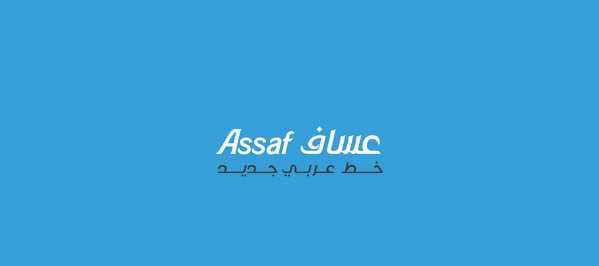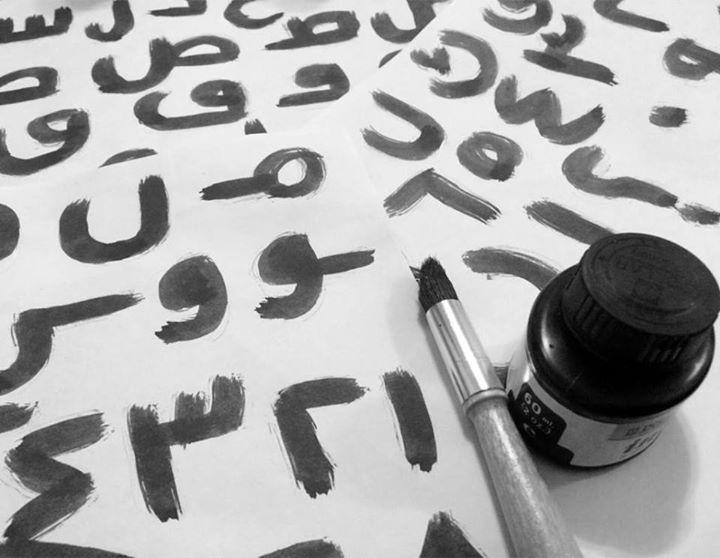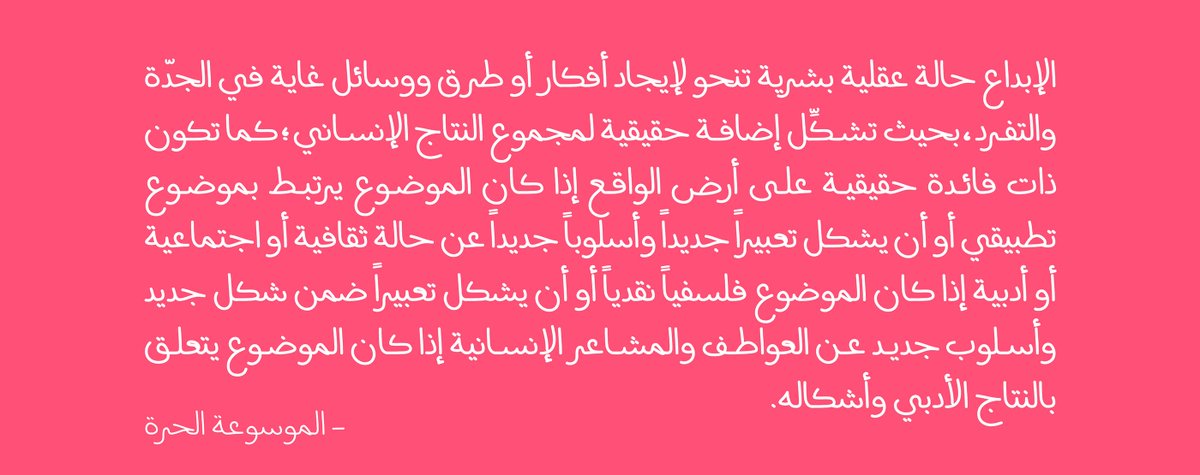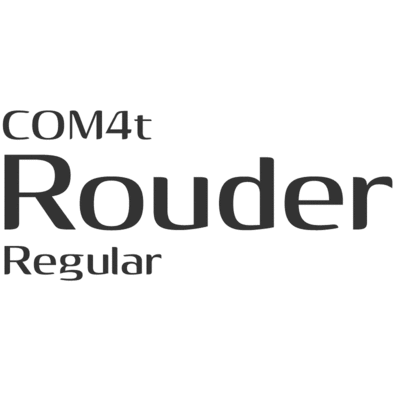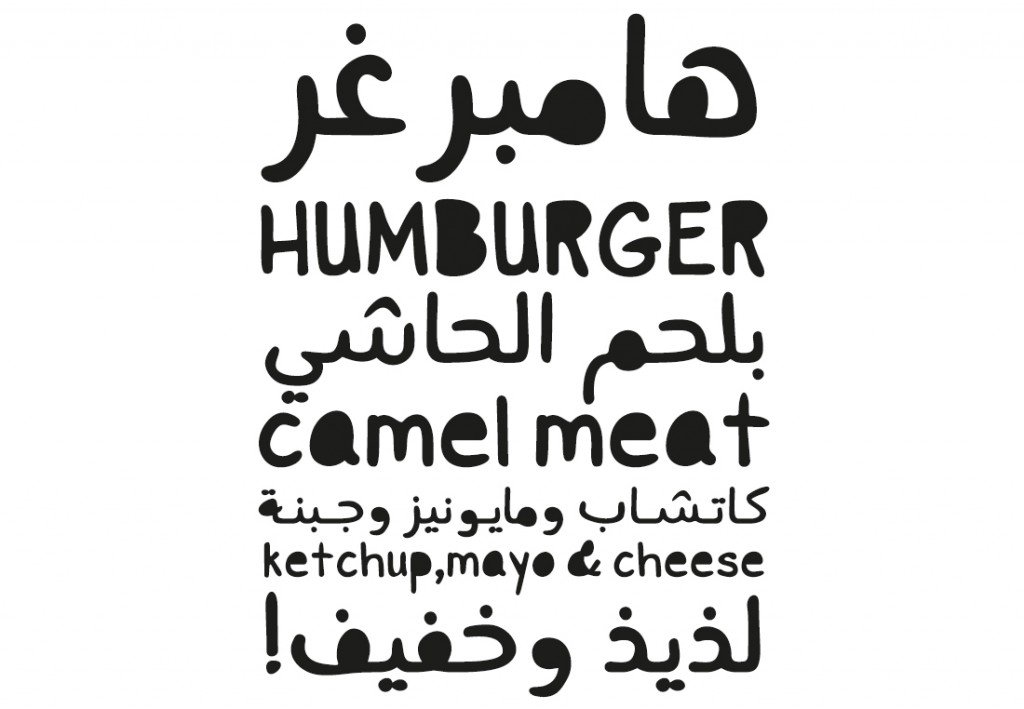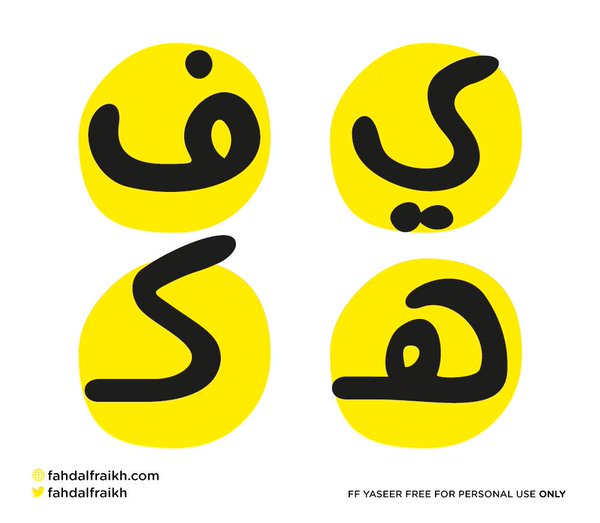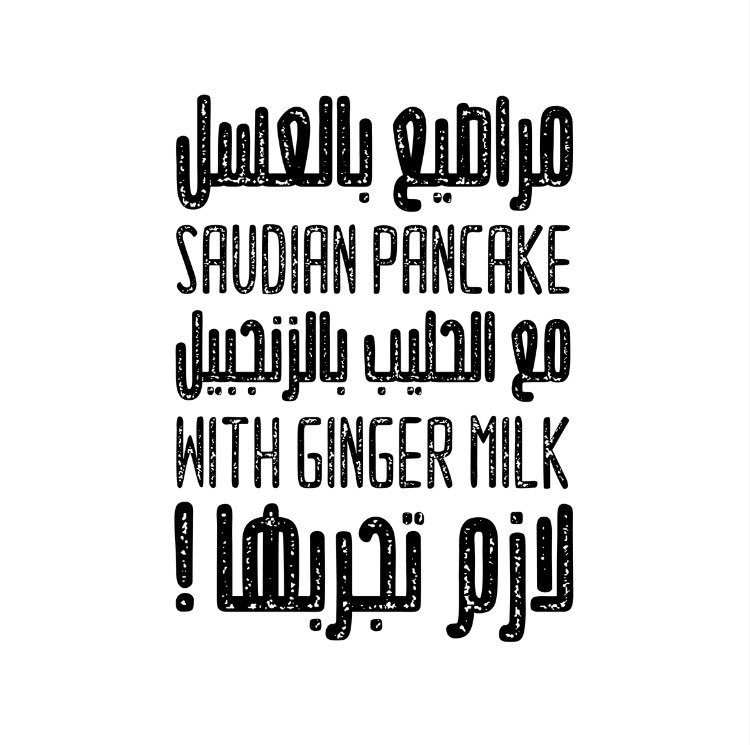
خطـــوط عربية وإنجليزية جميلة للتحميل المجاني، والمدفوع
خط عربي جديد للمصمم عساف القرني تحميل مباشر من هنا
خط ذياب تصفح من هنا جمالياته وأيضاً لشراءه
بوية | خط عربي بالفرشاة والألوان
(ملهم) خط عربي جديد، مستوحى من خذ اليد البسيط للتحميل
COM4t Rouder Regular
Yaseer Typeface
يسير .. خط مكتوب باليد
خط طويل | لـ فهد الفريخ
خط عربي مجاني مقدم من شركة وسم
خط مجاني ( ALEO ) نرجو أن ينال استحسانكم
خط طباعي ساخر صُنع من 76 علامة تجارية متميزة، من تنفيذ استوديو Hello Velocity الإبداعي.
خط مركزي من خطوط النسخ الجديدة المميزة
حكاية Hekaya
خط يدوي لـطيف يدعم العربية و اللاتينية، يتكون من ثلاثة أوزان: رفيع “مجاني” ،عادي وسميك
خطوط انجليزية جديدة يجب ان تمتلكهم
المبدع المغربي ياسر داحس
ينتج ثلاث خطوط عربية
خطوط جديدة مميزة
خط كوفام هو أحد خطوط مشروع الماتشميكنغ الخمسة للإصدار 2
تصميم وائل مرقص , آرثر شمال , والمهندس المعماري ريتشارد واغنر
عارف رقعة/ الخط الأكثر شعبية ودائما مايتم سؤالنا عنه
ويستفاليا / خط طباعي
تمت صناعته من وحي خط اليد
عدد كبير من الخطوط الانجليزية الرائعة
Gothical
خط سُكّر
تم تصميمه ضمن المزاوجة التايبوغرافية مع الخط اللاتيني "Overlock"
Exceed خط انجليزي مميز
خط كوفيان المميز
Kufyan Arabic Typeface
خط مميز مجاني